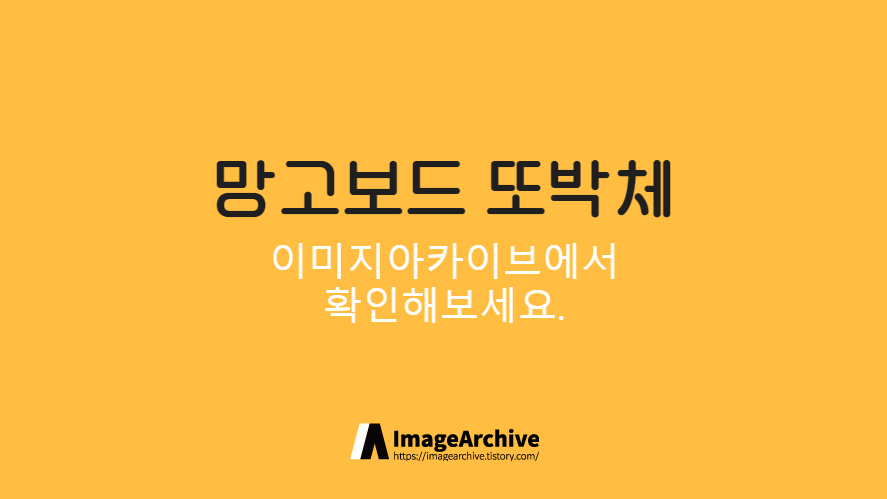
망고보드 또박체
폰트를 제작한 이유
망고보드 또박체는 디지털 콘텐츠 제작 플랫폼인 망고보드에서 사용자들이 다양한 디자인 작업을 수행할 때 활용할 수 있도록 개발한 서체입니다. 카드뉴스, 상세페이지, 홍보물, 동영상 등 다양한 콘텐츠를 제작할 때 일관된 디자인과 분위기를 유지하기 위해 자체적인 폰트를 제작하게 되었습니다. 이를 통해 사용자들이 통일된 브랜드 아이덴티티를 표현하고, 디자인 작업의 완성도를 높일 수 있도록 지원하고자 했습니다.
폰트 디자인의 특징
또박체는 반듯한 손글씨 느낌을 기반으로 한 서체로, 고딕체의 비율을 활용하여 가독성을 높였으며, 동글동글한 끝선 처리를 통해 귀여운 느낌을 부여했습니다. 또한, 빗침과 내리점의 여백을 적절하게 조절하여 글자 간의 균형을 맞추고, 전체적인 조화로움을 추구했습니다. 이러한 디자인 요소들은 깔끔하면서도 친근한 인상을 주어 다양한 디자인 작업에 활용하기 적합합니다.
폰트 사용 용도
또박체는 다양한 디자인 작업에 활용할 수 있는 범용 서체입니다. 브로슈어, 포스터, 책, 잡지 등 인쇄물부터 웹페이지, 광고 배너, 이메일, 전자 브로슈어 등 디지털 콘텐츠까지 폭넓게 사용 가능합니다. 또한, 영상물의 자막이나 영화의 오프닝 및 엔딩 크레딧, UCC 등 영상 콘텐츠에도 활용할 수 있으며, 판매용 상품의 패키지 디자인이나 웹사이트 및 프로그램 서버 내 폰트 탑재, 전자책 제작 등 다양한 분야에서 활용할 수 있습니다.
폰트 미리보기